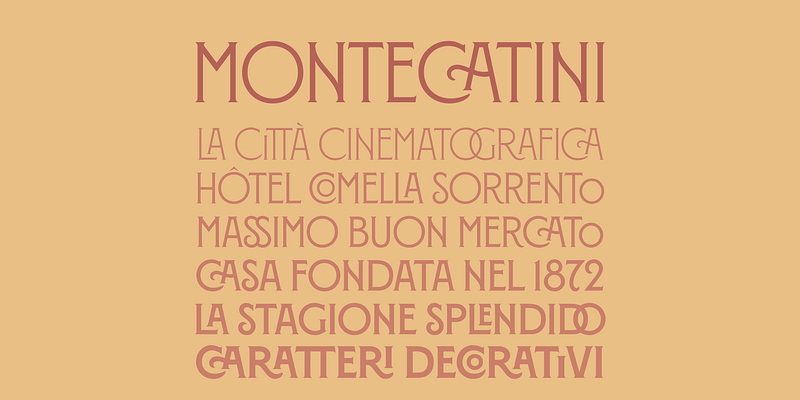
Montecatini tire son inspiration des élégantes affiches de voyage de Stile Liberty en Italie au début des années 1900. La famille de 24 modèles s’étend sur 6 poids et 4 largeurs pour créer un système typographique dynamique. Caractéristiques du mouvement Art Nouveau, les ligatures distinctives de Montecatini procurent une touche de flair, tandis que sa largeur et son poids permettent un ajustement dynamique.